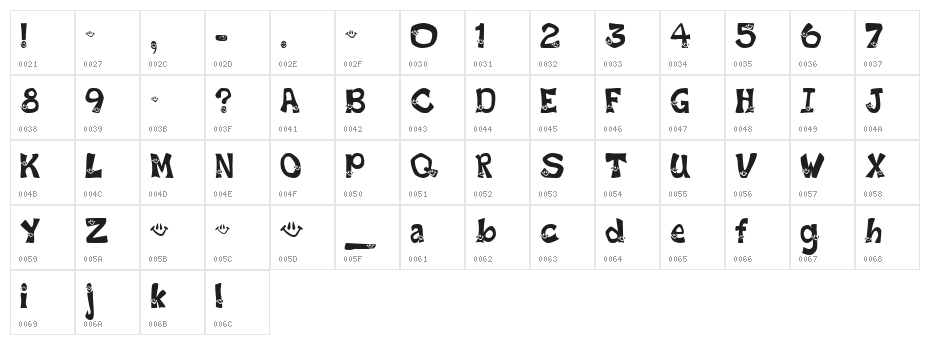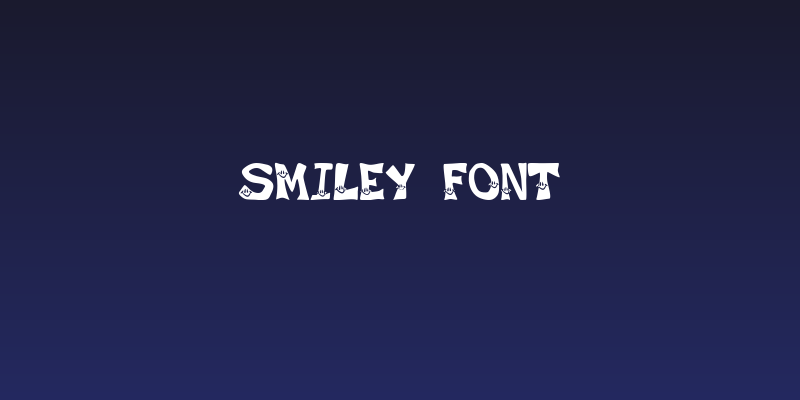
Smiley Font Font
| Stil general | Playful, Whimsical |
| Caz de utilizare | Headlines, Logos, Decorative Text |
| Proiecte propuse | Ideal for children's books, party invitations, playful branding, and any project needing a fun and engaging look. |